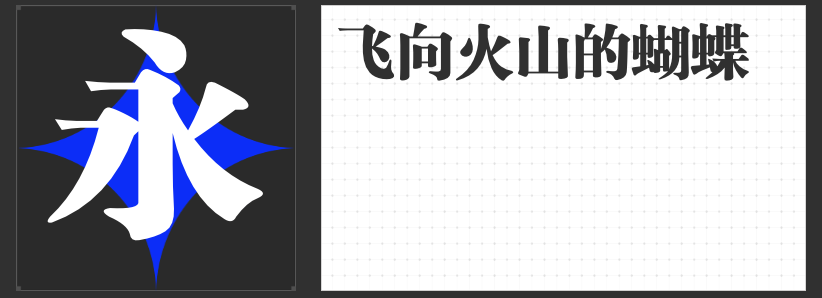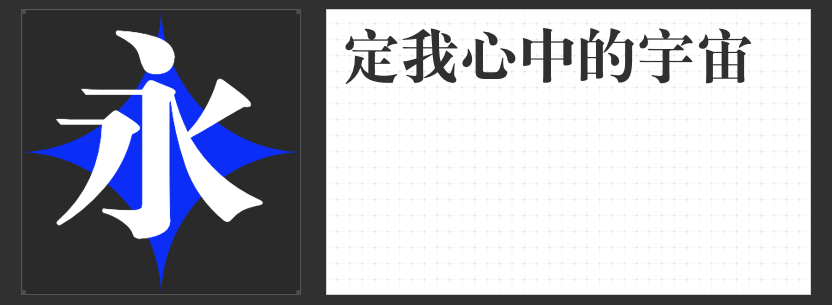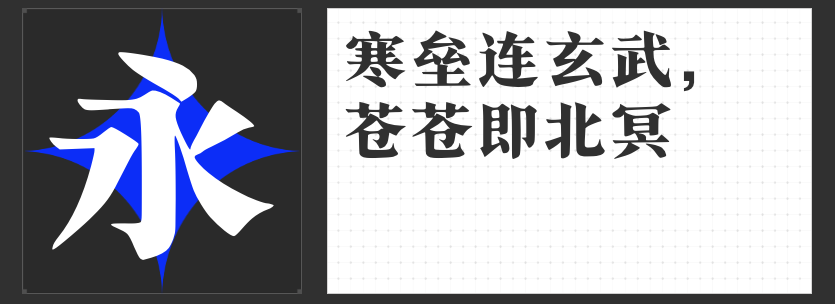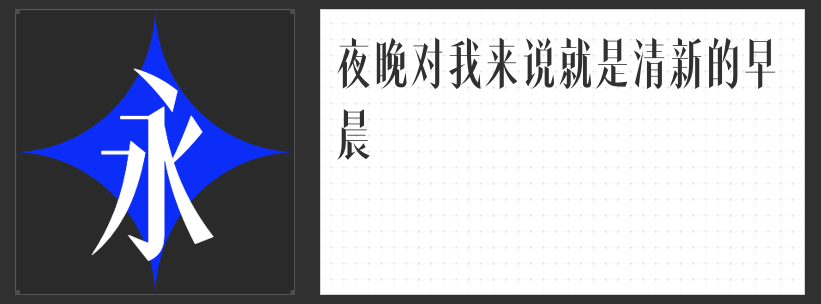
海报视觉进阶指南:四款宋体变奏字体重塑设计张力
在海报设计的视觉博弈中,字体选择往往决定着信息传递的效率与美学层次。以下四款突破传统宋体框架的创新字体,以独特的结构语言与风格表达,为设计师提供差异化解决方案。
一、励字大标宋简繁
这款融合老宋体与黑体特质的字体,通过横细竖粗的对比强化视觉节奏,末端三角装饰则延续了雕版印刷的工艺美感。其创新之处在于将黑体的几何理性注入宋体结构,使笔画转折处呈现刚柔并济的张力。在需要传递文化厚重感的海报场景中,这种“新古典主义”设计既能保持传统书法的骨法用笔,又通过简化的装饰元素提升现代阅读舒适度。
二、高手兵克高雅宋
以1:1.6的极致长宽比突破常规宋体比例,这款字体通过笔画末端的尖角处理与竖画收笔的向左切口,构建出独特的动态平衡。其设计哲学在于用几何化的装饰语言替代传统衬线,在保持宋体识别特征的同时,赋予文字轻盈的视觉流动性。特别适合竖版海报标题设计,瘦长的字形结构能有效引导视线纵向延伸,强化信息层级。
三、机甲宋玄武号
将宋体结构与机甲元素进行解构重组,这款字体通过45度斜切笔画与金属质感装饰线,创造出具有未来感的视觉冲击。其创新点在于保留宋体横细竖粗的基本框架,但用机械齿轮般的转折处理替代传统书法笔意。在科技产品或游戏海报中,这种“硬核书法”风格能同时传递文化底蕴与前卫气质。
四、励字新粗宋简
通过压缩字身高度至传统宋体的70%,这款字体以横向扩张的布局打破竖排文字的惯性思维。其设计亮点在于将装饰性衬线转化为结构支撑元素,使横画末端的三角装饰同时承担功能性与美学双重使命。在需要强调视觉宽度的海报场景中,扁方结构能有效占据空间,形成强烈的版面存在感。
这四款字体通过结构比例调整、装饰元素重构、风格基因融合等创新手段,在保持宋体识别特征的同时,拓展了海报设计的表达维度。